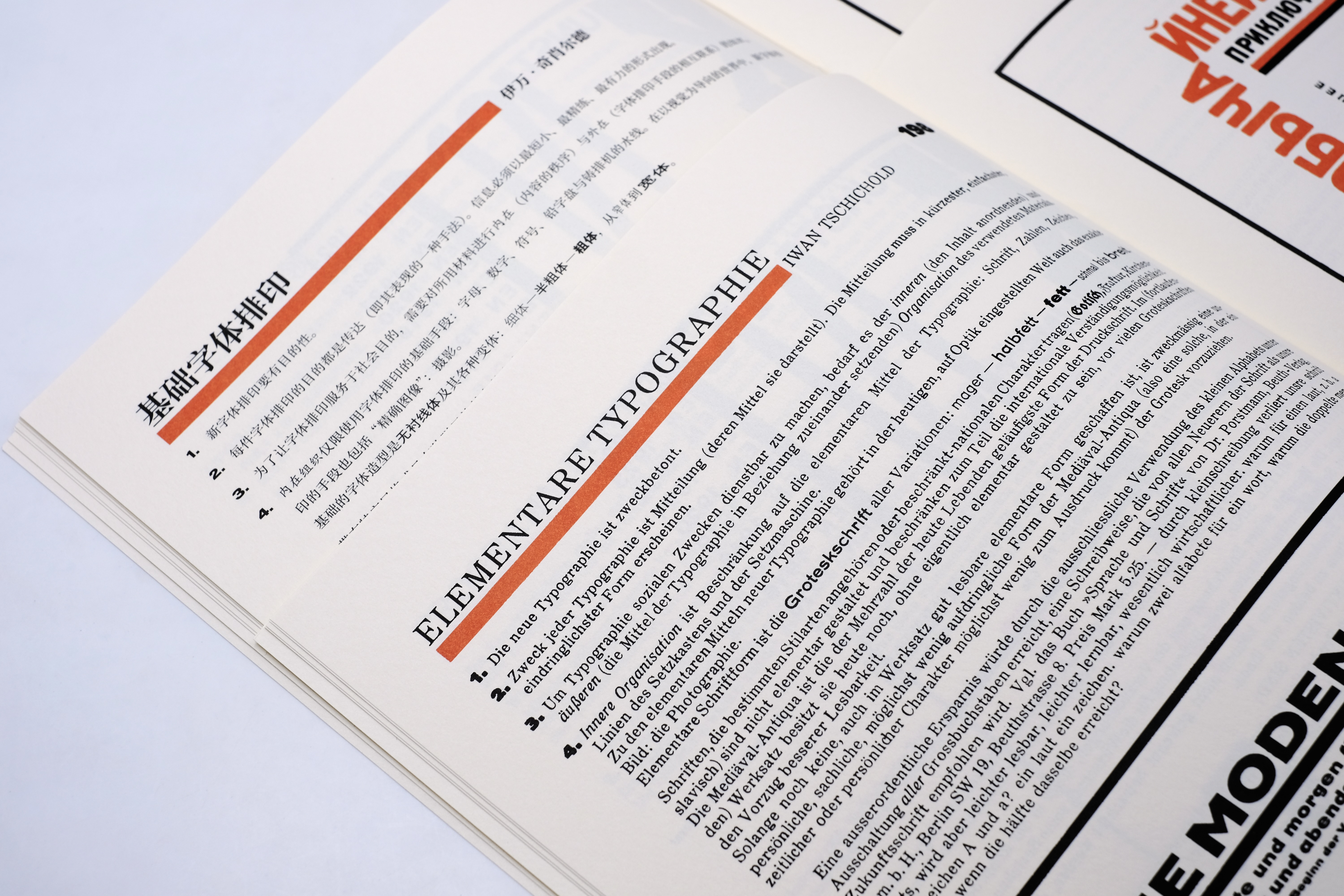
字体排印通信·基础字体排印
[德]伊万·奇肖尔德编,刘庆(Eric Liu)译
在「1923 年包豪斯展」举办两年后,扬·奇肖尔德(Jan Tschichold,1902—1974)受邀担任《字体排印通信》(Typographische Mitteilungen)杂志 1925 年 10 月刊的客座编辑,主持策划了这期题为「基础字体排印」的特刊。该刊最初计划以包豪斯为主题,最终整期围绕「新字体排印」展开——刊名首次采用小写字母排版,全刊采用红黑双色印刷,旨在向职业印刷师、排版工与字体设计师展示新字体排印的原则。当时德国主流的排版方式仍以传统的对称排版为主,因此「基础字体排印」特刊一经问世便引起轰动与争议。年仅二十三岁的奇肖尔德由此成为「新字体排印」运动的代表人物和核心推动者。
本书中文版译自该特刊,收录了包括其本人在内的多位先锋人物的文章与作品,如莫霍利–纳吉·拉斯洛、埃尔·利西茨基、赫伯特·拜尔、库尔特·施维特斯等。通过这些选文与作品,读者得以窥见二十世纪初的设计先驱们如何回应新技术与新世界——其思考在今日仍具启发意义。
奇肖尔德在本书原版扉页署名「伊万·奇肖尔德」,实为将其教名「约翰」的德语变体「扬」改成俄语变体「伊万」,折射出当时对俄罗斯先锋派的推崇。为尊重原貌,中文版保留此译名。
原刊不仅是内容重要的文献,更是平面设计史上的标志性作品。因此,在中译本制作过程中,我们不仅力求翻译忠实、表达规范,而且尽可能保留原刊的版式及视觉风格,通过对应原版的字体与版式,在中文语境中延续原刊设计气质。
为方便读者对照阅读与欣赏,随书附赠原刊复刻版。
原刊出版于二十世纪二十年代,部分内容与现行出版规范有所不同,编校时已作调整。然囿于编校之繁,疏漏难免,恳请读者指正。
• 原题:Typographische Mitteilungen: Elementare Typographie
• 原编者:[德]伊万·奇肖尔德
• 翻译:刘庆(Eric Liu
• 字体:方正字库